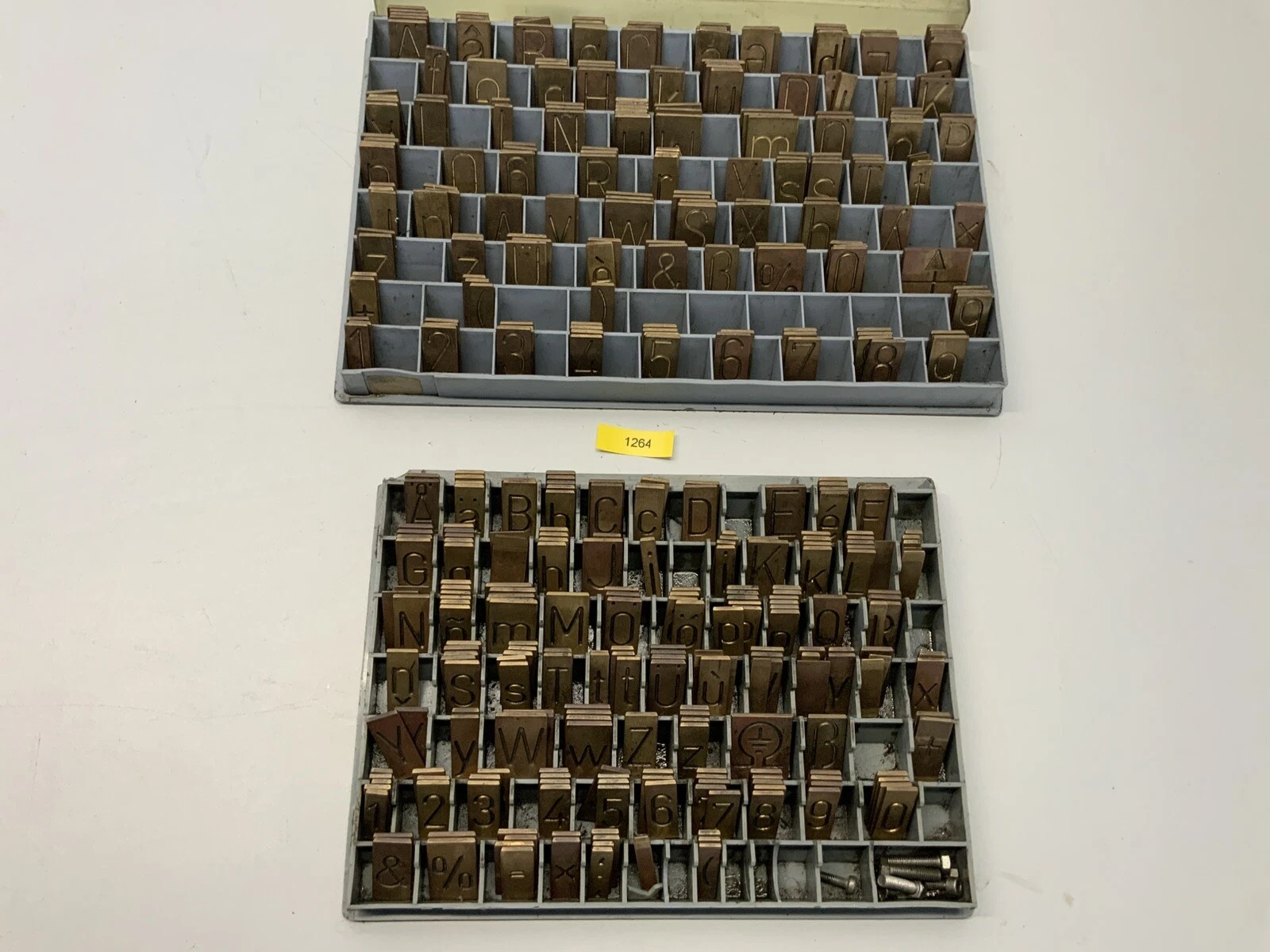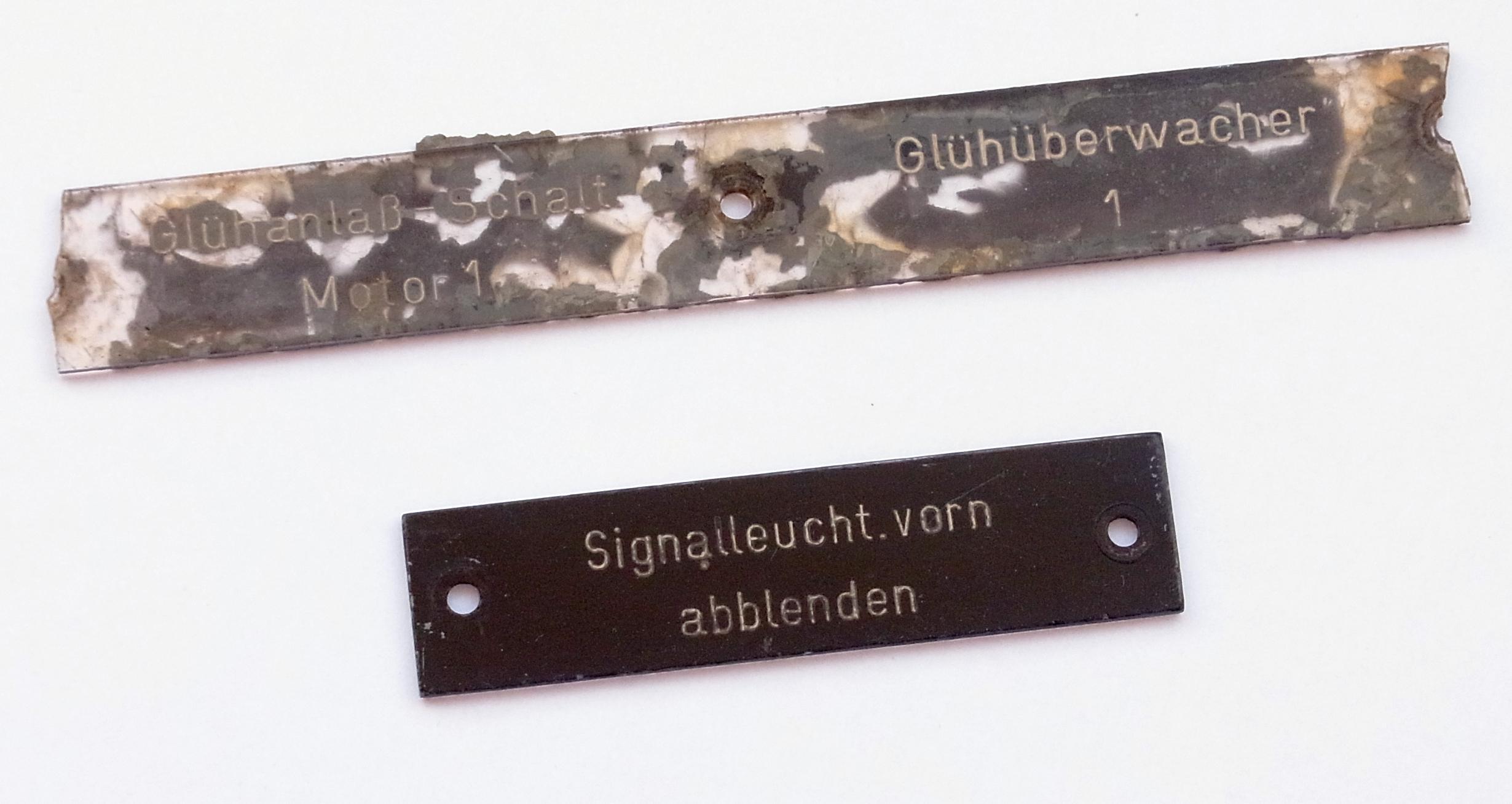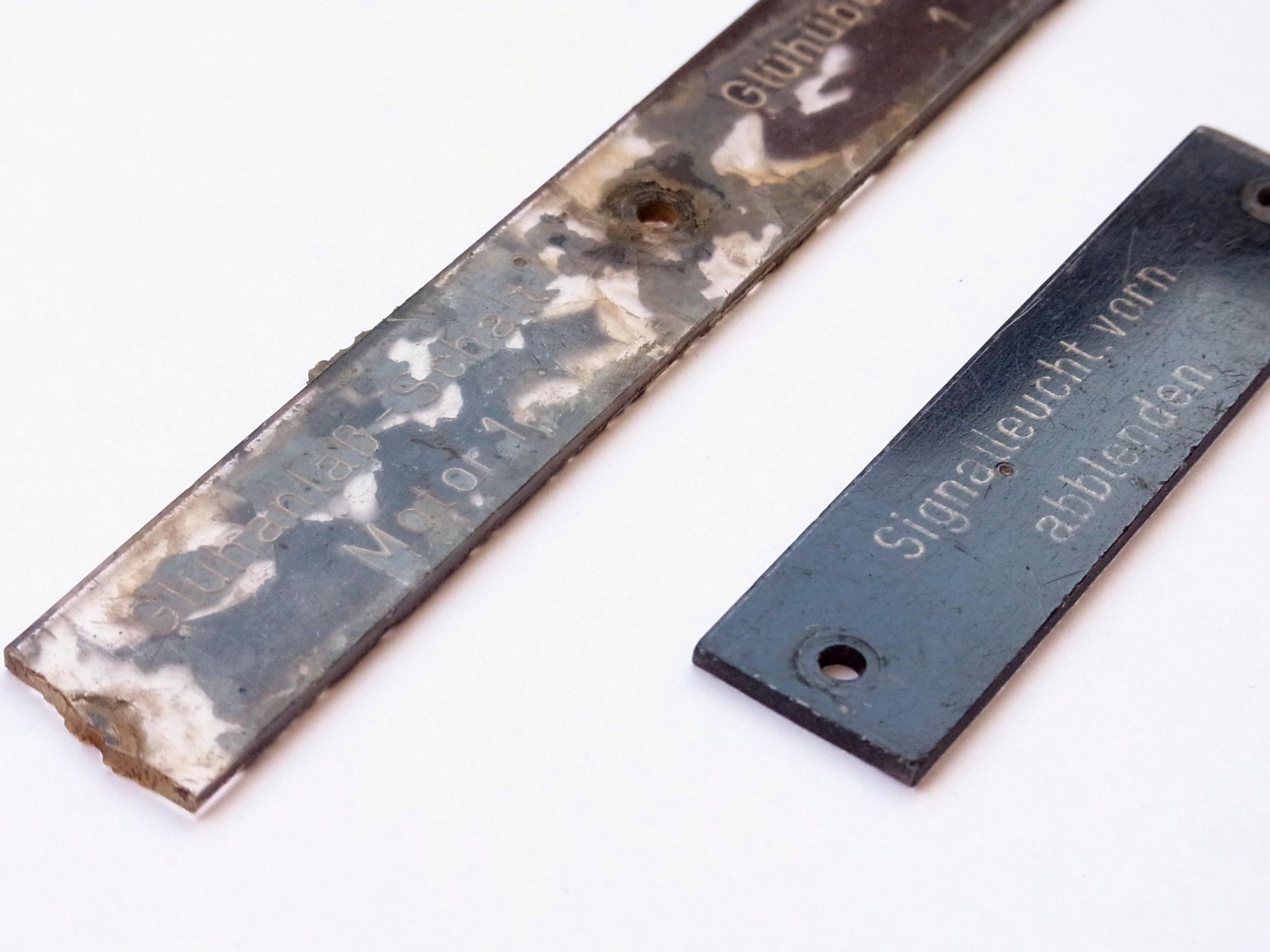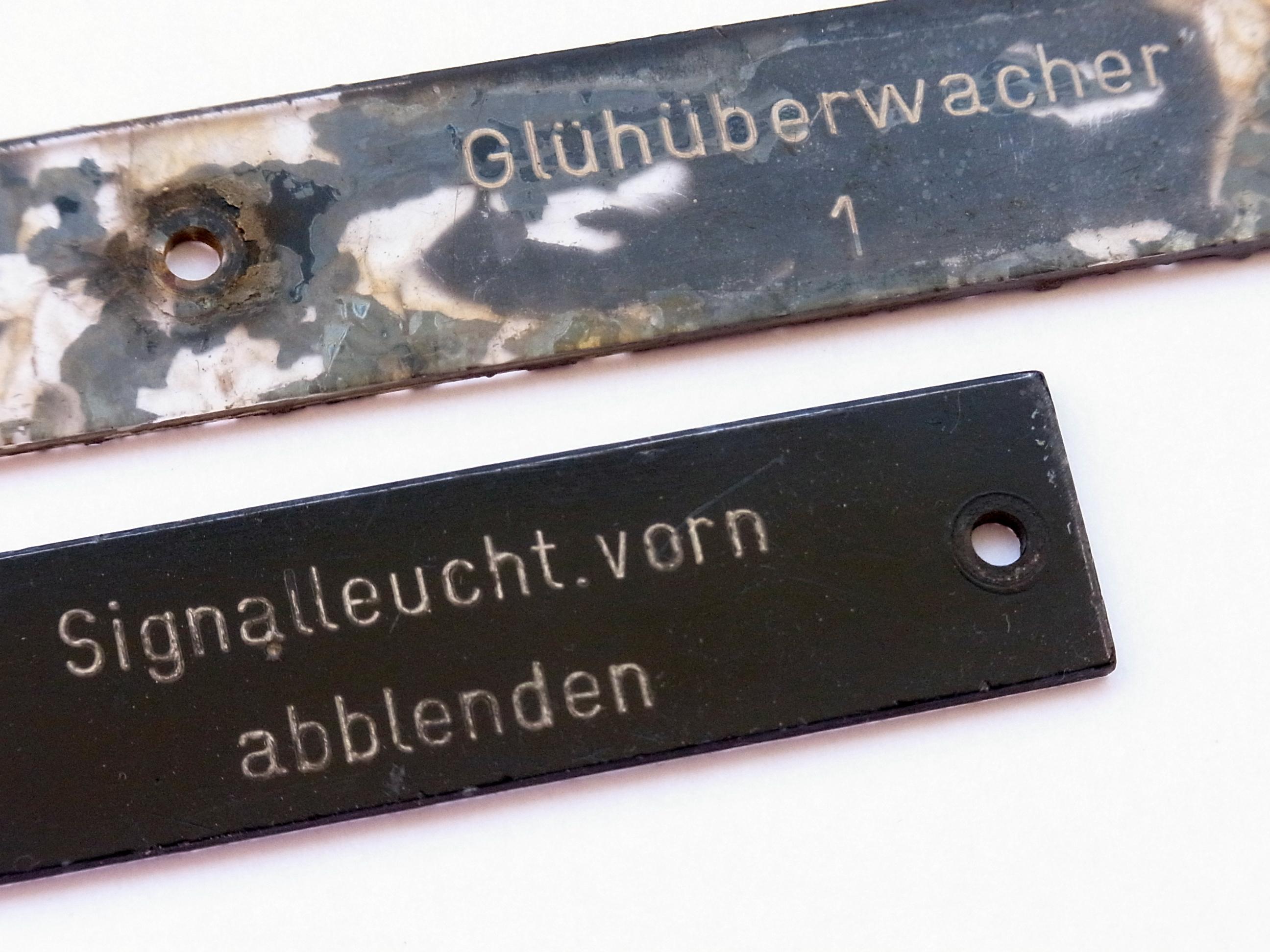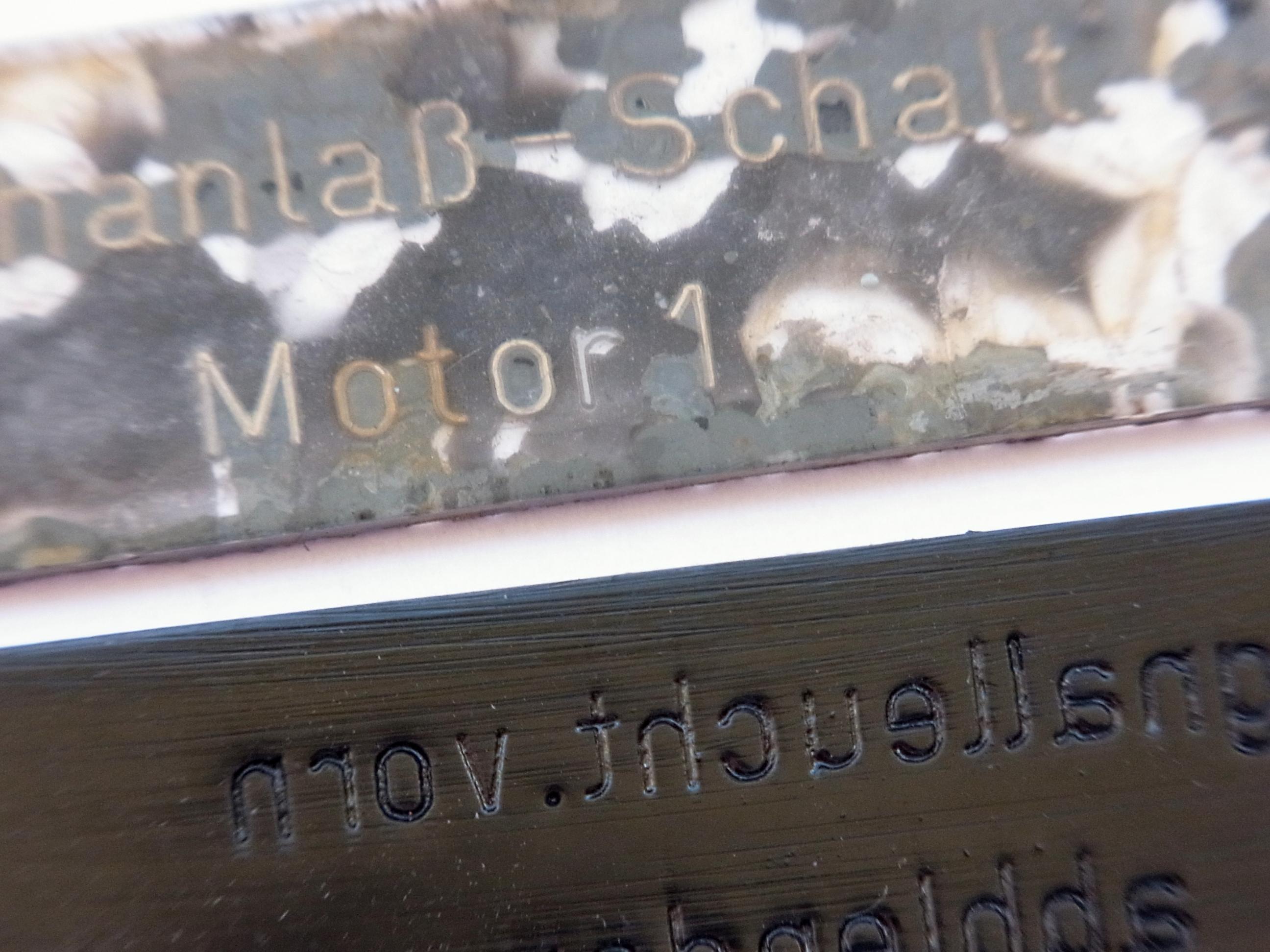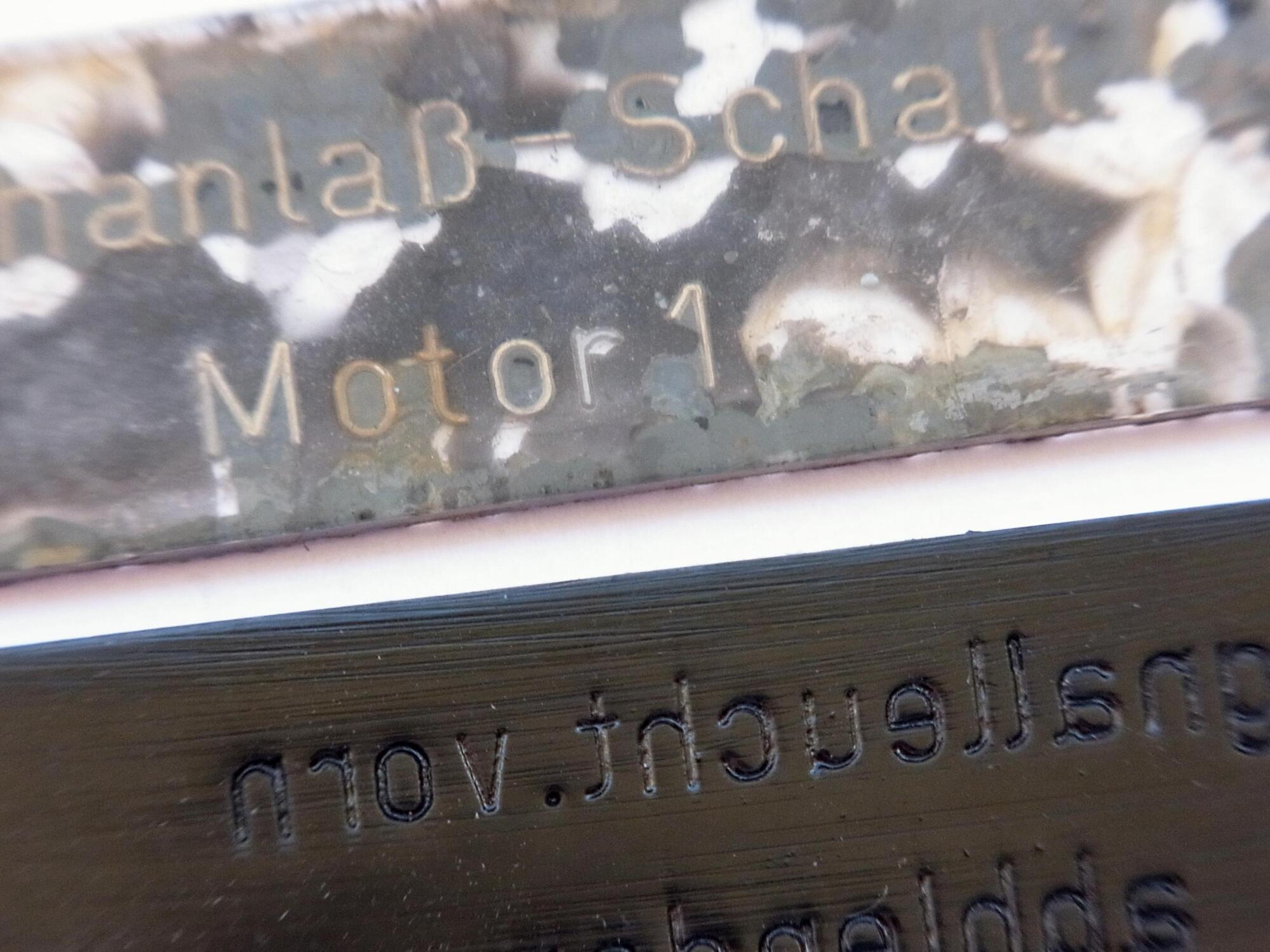
Schriftgravur für Kunststoffschilder – 1964
Diese Schilder sind vom Führerstand einer Lokomotive Baujahr 1964, sie sollen im Zuge der Restaurierung erneuert werden.
Oberes Schild: Befundzustand. Unteres Schild: original, aufgearbeitet.
Einige der Schilder müssen aufgrund des schlechten Zustandes neu hergestellt werden.
Die Frage ist: mit welchem System od. Gerät wurden diese Gravuren damals hergestellt?
… es sieht aus wie eine maschinelle Fräsung, der Zeichensatz ist wohl eine Art traditionelle ›Normschrift‹ oder evtl. mit der DIN verwandt. Hier noch eine Nahansicht:
Die Auslage sieht so zumindest aus, als wären die zu so etwas in der Lage. Aber vielleicht sind das auch nur Reliquien aus Opas Zeiten  …
Opas Zeiten stimmt schonmal … Ich erinnere mich auch, bei einem Schildermacher/Graveur alter Schule Gravuren der Art gesehen zu haben. Und die Schriftart paßt auch. Müßte man also einen Graveur finden, der evtl. noch solch eine Maschine betreibt.
Die Abb. des Gravographen (tolles Wort) stammt woher? Ist die Maschine noch irgendwo in Betrieb?
Graveure arbeiten mit Ein-Linien-Schriften und der Gravuerstichel beeinflusst die Strichbreite. Einfach mit den Schildern zu einem Stempel und Schilder Graveur gehen. Dieser sollte eine Oberfräse aka Graviernaschiene haben. Diese werden in der Regel für verschiedene Metalle verwendet. Lasergravur ist dafür nicht geeignet.
Es könnten auch gedrückte Schilder sein die wurden mit Stahstempel hergestellt. Manchmal findet man auf Ebay und Kleinanzeigen Schriftsätze. Allerdings sind die Drückmaschienen kaum zu finden.
Nicht zwingend, es ist nur die einfachste Variante. Flächen gehen auch, machen aber natürlich mehr Arbeit.
Das war bezogen auf die Frage zu den Schildern.